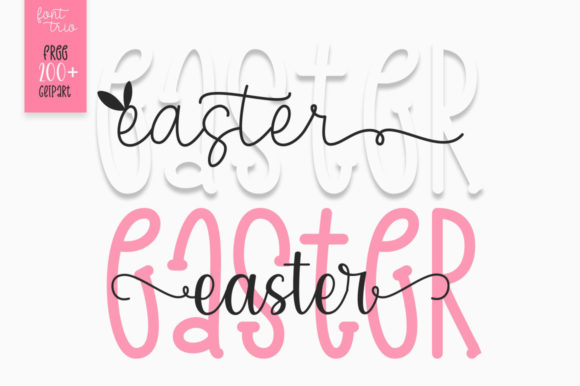
Easter
إذا كنت تبحث عن أصول عالية الجودة مثل Easter، فإن هذه الحزمة المميزة هي خيار رائع لمشاريعك الإبداعية.
سواء كنت تقوم بإنشاء منتجات الطباعة عند الطلب أو دعوات الزفاف أو رسومات وسائل التواصل الاجتماعي، فإن Easter هو الخيار المثالي.